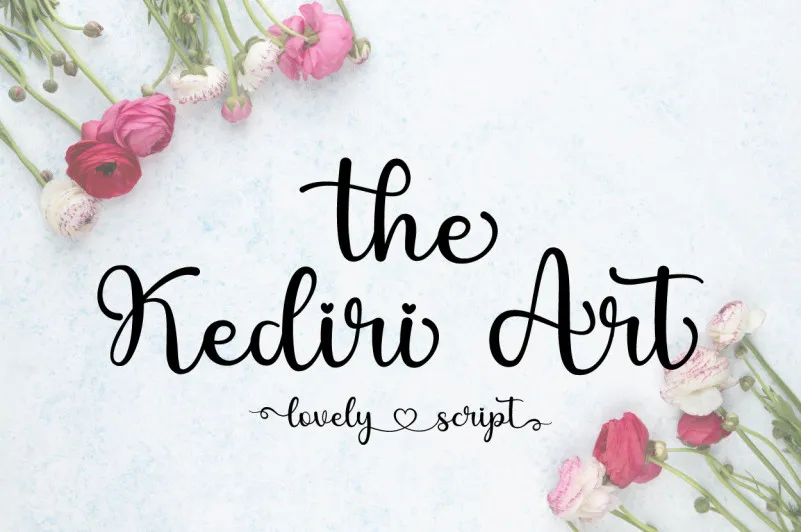
A fonte The Kediri Art Font é uma jóia do mundo da tipografia, perfeita para quem valoriza a arte plasmada no papel e deseja dar vida à sua escrita através de formas únicas e vibrantes. Ela foi criada pelo talentoso designer sugiharto1790 e oferece uma experiência única ao adquirir ou utilizar essa fonte, destacando-se como um recurso valioso para artistas, designers gráficos e apaixonados por letras. Com The Kediri Art Font, você não apenas abre as portas a uma nova forma de expressão visual, mas também se beneficia do trabalho cuidadosamente elaborado por sugiharto1790. Esta fonte é ideal para adicionar um toque único a qualquer projeto gráfico que você estiver desenvolvendo – seja ele um poster com texto em estilo artístico ou uma ilustração cheia de personalidade. O uso desta fonte não só torna seu trabalho mais autêntico e individual, mas também oferece uma oportunidade para explorar o poder da arte no design. A The Kediri Art Font é mais do que apenas letras; ela traz vida e expressão a cada palavra escrita com ela. Para aqueles que amam criar algo novo e significativo através de suas habilidades de artes gráficas, esta fonte é uma peça essencial na sua coleção. Adquirindo The Kediri Art Font, você não apenas adquire uma ferramenta útil para seu trabalho diário; você também se une a uma comunidade que valoriza e promove a arte da tipografia. Esta fonte é a concretização de um desejo por expressão criativa, oferecendo aos amantes do design uma maneira elegante de transformar seus pensamentos em letras vivas, prontas para serem usadas no mundo real.